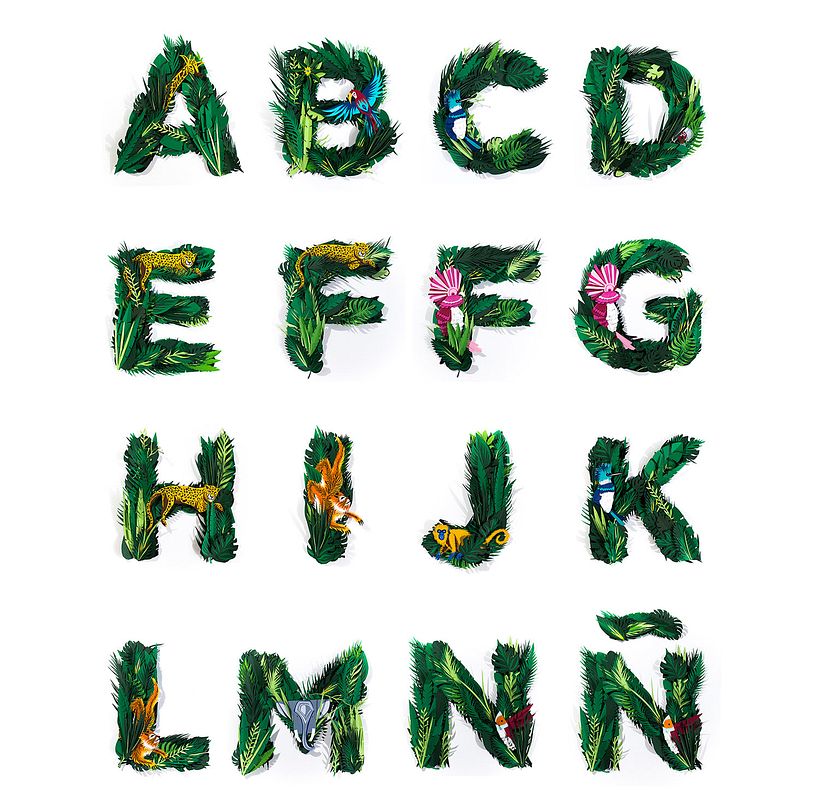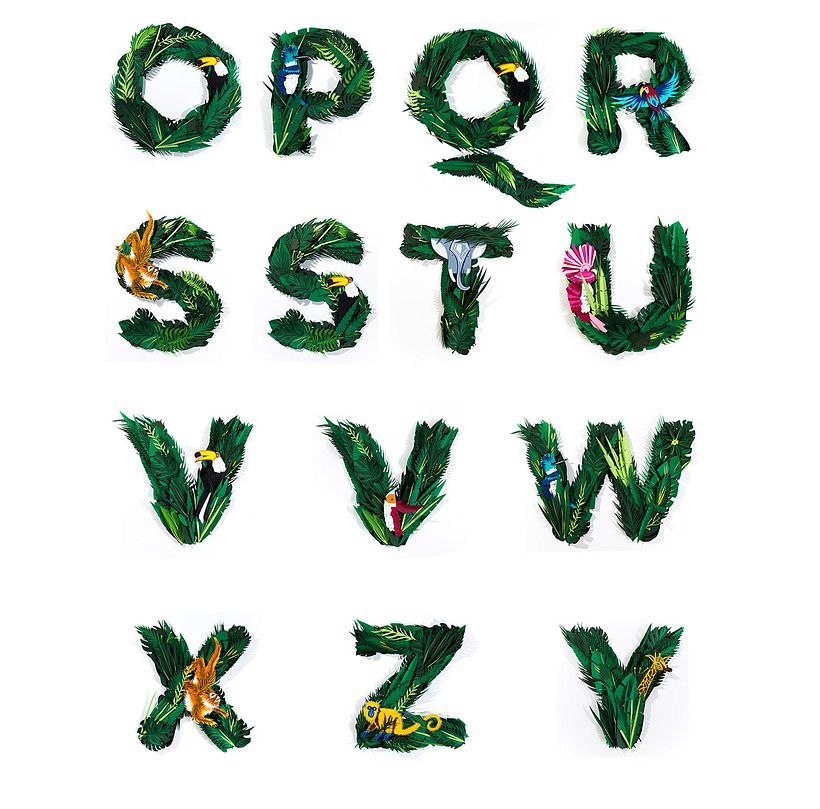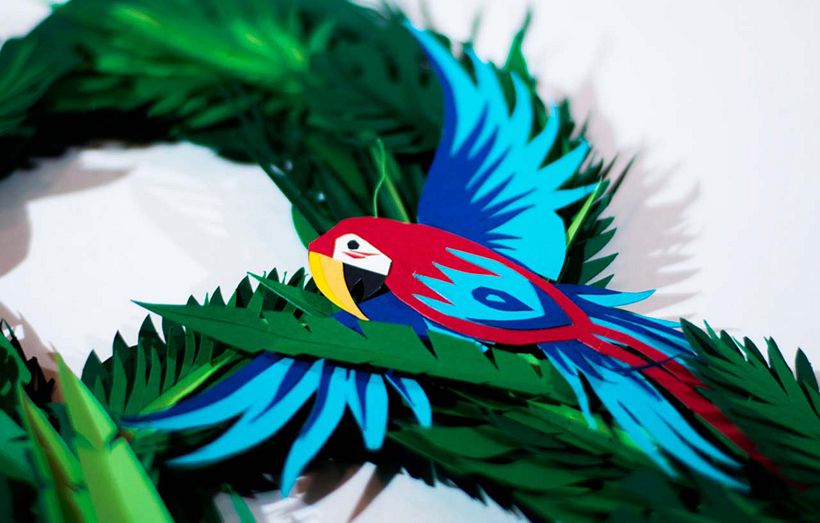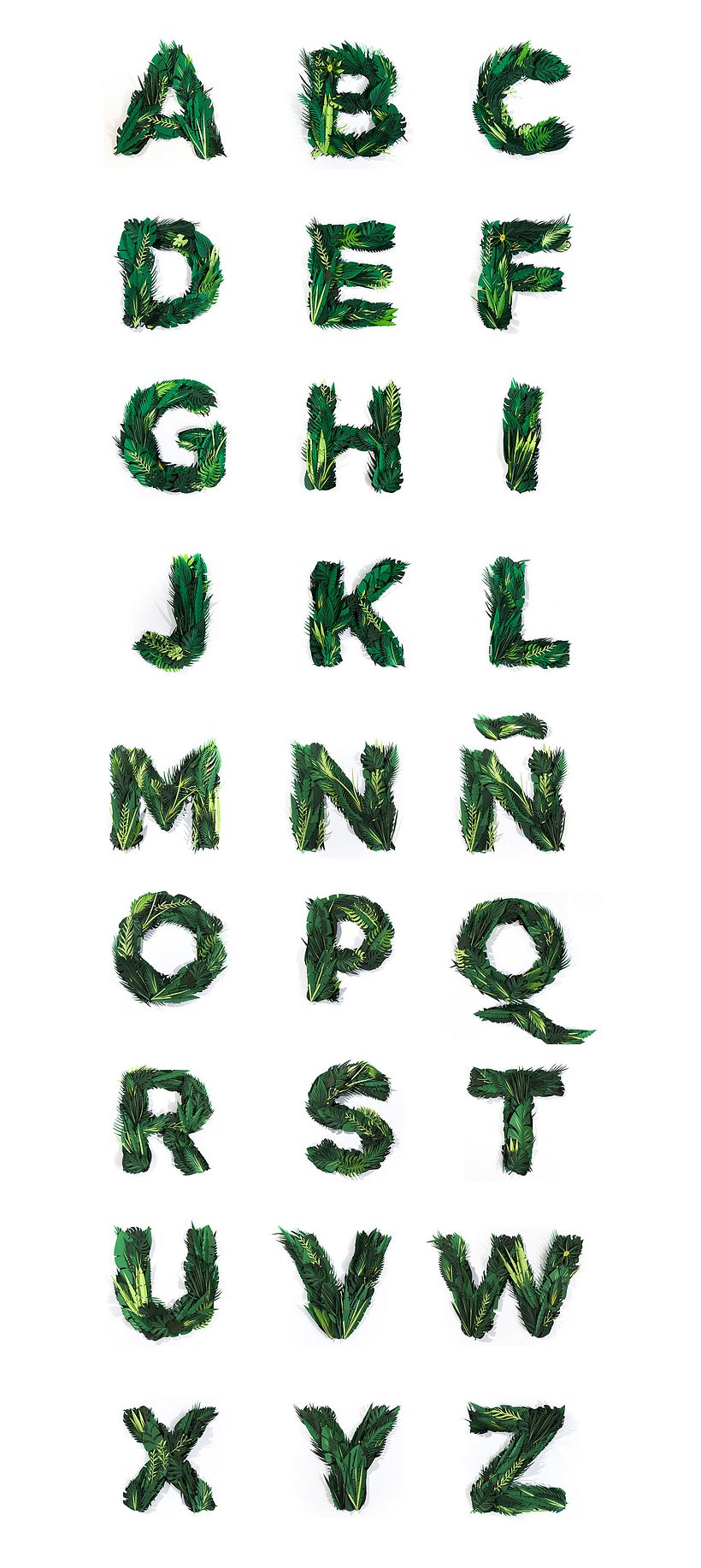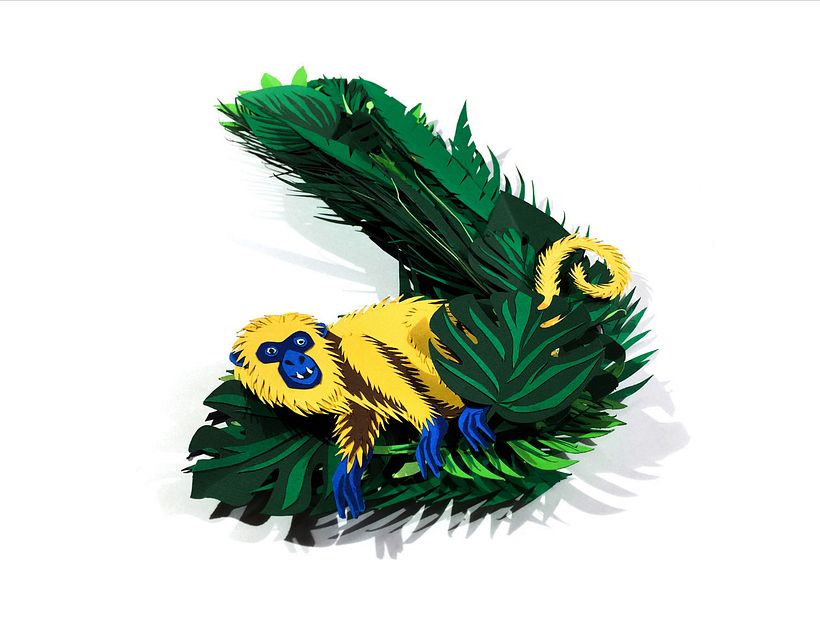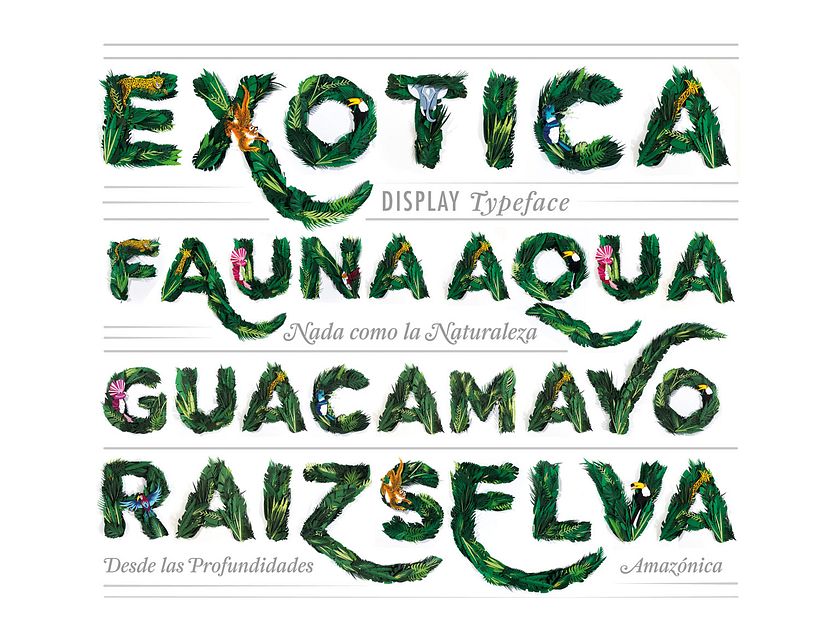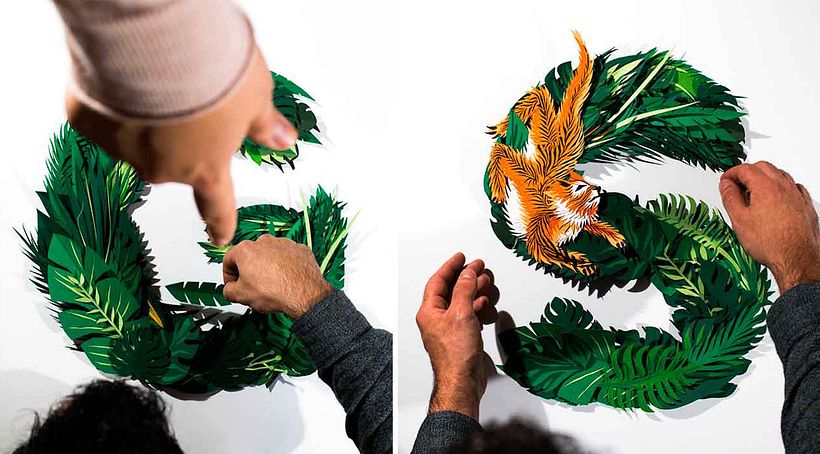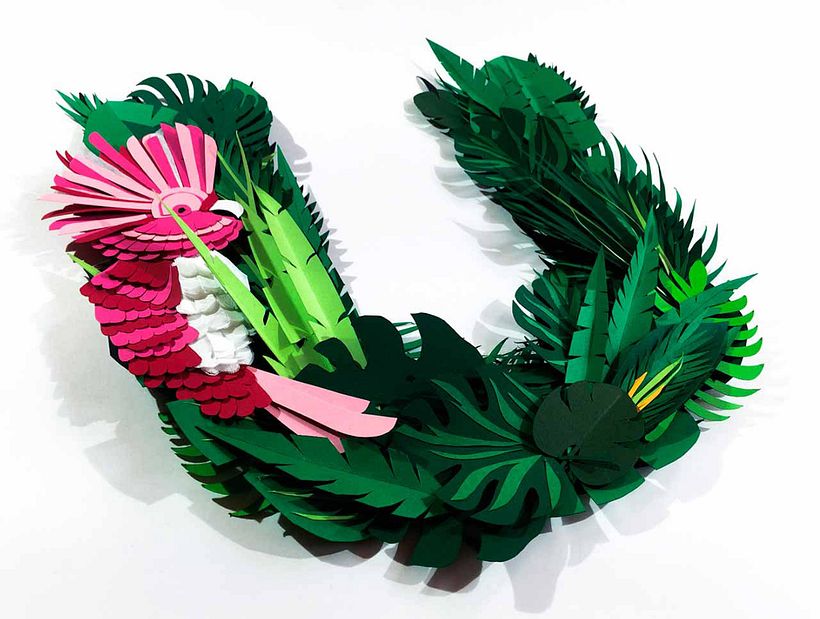
Tipografía y papercraft con sabor tropical
Tupida vegetación amazónica creada a base de papel es el ingrediente principal de una tipografía Exótica.
Inspirada por la selva amazónica, Inés Marco Aguilar (@inesmarco__), Berta Picó y Luis Utrillas han diseñado y llevado a cabo de manera completamente artesanal, una tipografía display que emula la vegetación tropical, tupida y densa gracias a los riegos del río Amazonas. Exótica es un proyecto que aúna tipografía, lettering y craft, pues cada una de las hojas que componen las letras ha sido dibujada, recortada y colocada a mano.
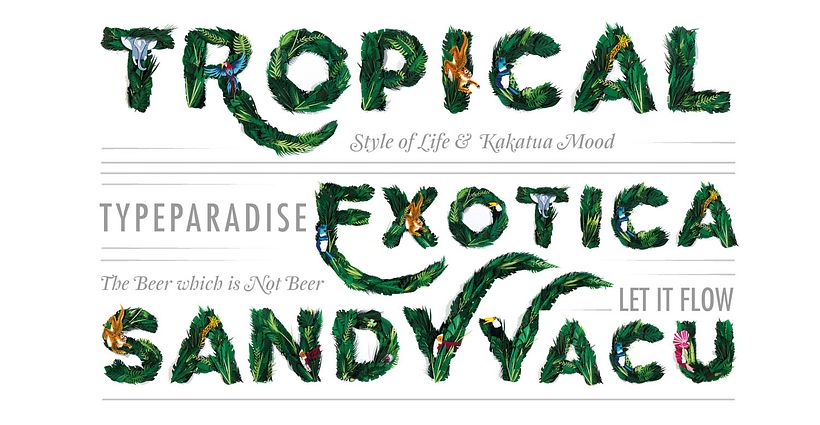
Exótica está compuesta por un set de glifos con variables. El equipo formado por Inés Marco, Berta Picó y Luis Utrillas diseñó y realizó un abecedario completo utilizando únicamente la vegetación como elemento para componer la tipografía y recreó animales tropicales para crear las variables, sumando color al conjunto.
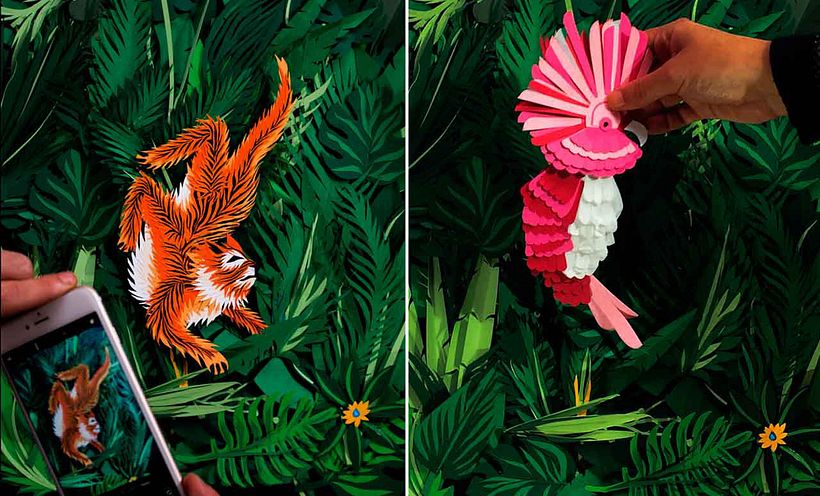
El proyecto de la tipografía Exótica nació como un ejercicio planteado a los alumnos de la Escuela Superior de Diseño de Aragón y el resultado es realmente profesional.